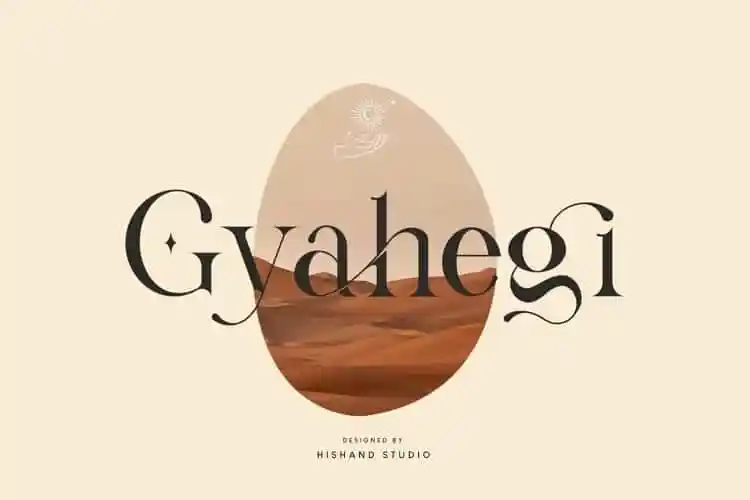
Gyahegi Serif Font – Download Grátis
A Gyahegi Serif Font é uma elegante tipografia serif que oferece valor com belas ligaturas. Seu design foi elaborado pelo Hishand Studio e compartilhado, garantindo um pacote de qualidade repleto de beleza gráfica e simetria. Essa fonte é perfeitamente adequada para aplicação em logotipos de marca, anúncios, embalagens de produtos, postagem nas redes sociais, roupas de marcas, cabeçalhos de revistas e muitos outros usos visuais. Com sua proposta de design moderno mas sofisticado, a Gyahegi Serif Font se destaca como uma escolha versátil para diversos cenários gráficos em seu catálogo. Engajante e prática, ela certamente encaixa-se perfeitamente no dia-a-dia dos designers digitais que valorizam tanto o charme quanto a funcionalidade de uma fonte serif.